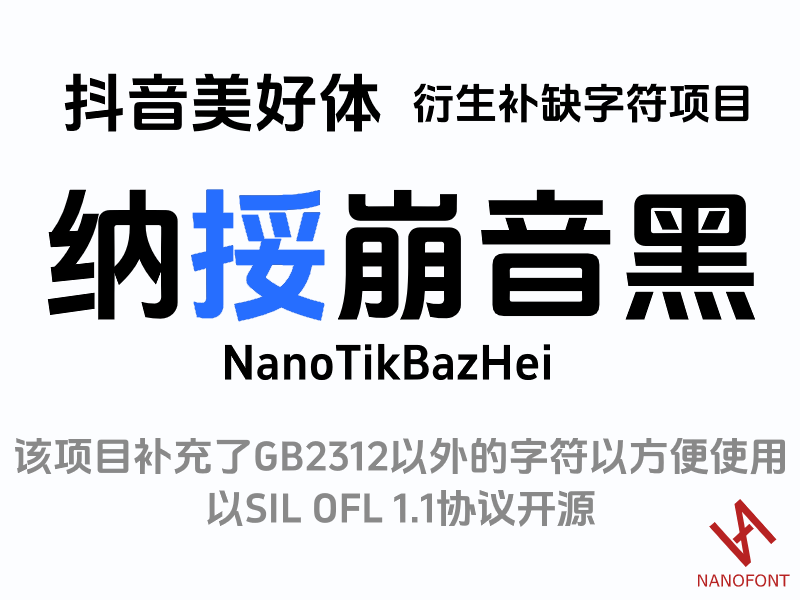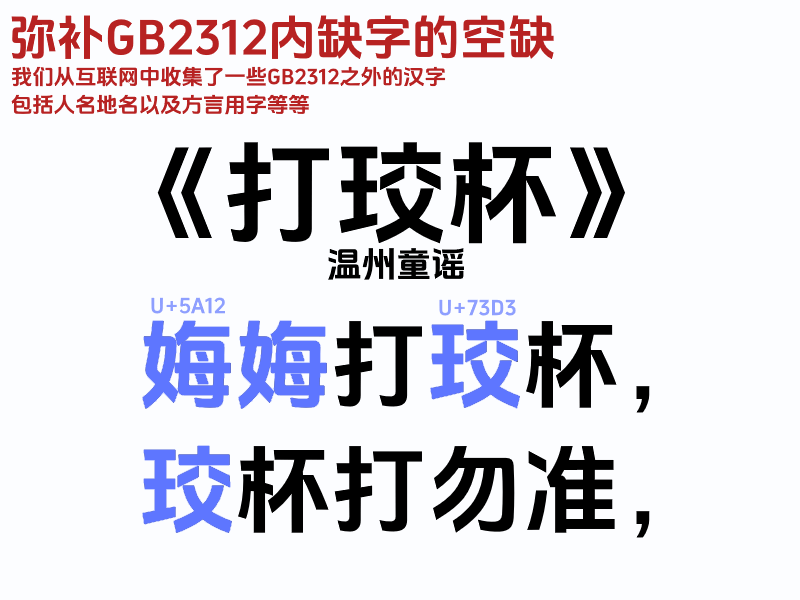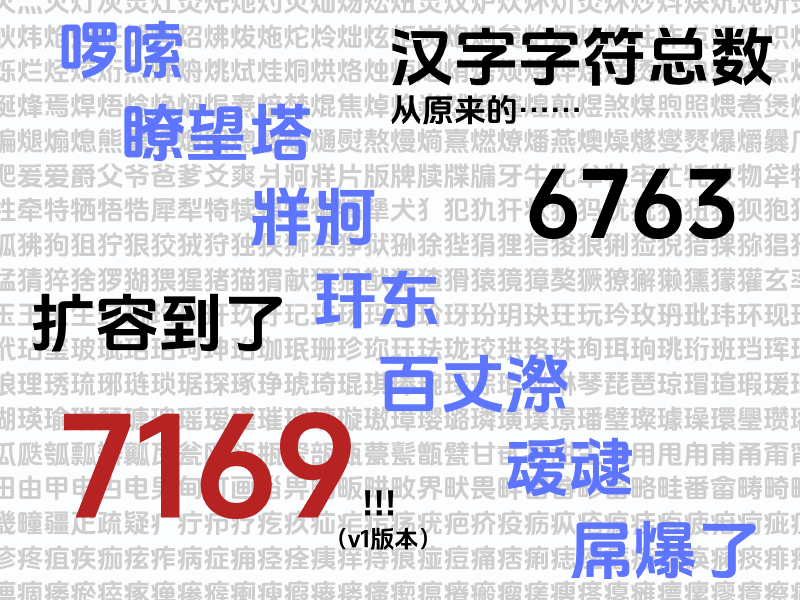
抖音美好体衍生补缺字符项目纳捼崩音黑NanoTikBazHei,补充GB2312以外字符,SIL OFL 1.1协议开源,NANOFONT-刊刻Kntuk
该款字体的源头要回溯到2023年上线的抖音美好体,这是方正携手抖音共同打造的作品,并明确采用了OFL开源协议向大家开放。不过它的底层架构只覆盖了基础的GB2312字符集,码位相对固定。我在平时剪视频配字幕的过程中慢慢摸出规律来,只要文本里混进几个稍微冷门或结构复杂的汉字,屏幕上就会直接跳出缺字方块或者突然切回系统默认字体,整体的排版节奏容易被打断。虽然开源许可本身鼓励二创,但实际上愿意花时间往里填字、做扩展的团队确实寥寥无几。既然缺口摆在眼前,我们就干脆顺着这条线往下走,把反复露出来却显示不出来的字形一个个找参考、对比例、做替换。经过几轮持续的收集与微调,最终把这些缺失的部分全部缝合整合,就做成了目前拿出来的这个完整方案——纳挼崩音黑。
为弥补GB2312缺字,从互联网收集了人名地名及方言用字等。以温州童谣《打珫杯》为例,“姆”(U+5A12)和“珫”(U+73D3)是GB2312外的汉字,童谣内容为“姆姆打珫杯,珫杯打勿准”。-刊刻Kntuk
汉字字符总数从6763扩容到7169(v1版本),展示了啰嗦、瞭望塔、牂牁等汉字,配文“屌爆了”。-刊刻Kntuk